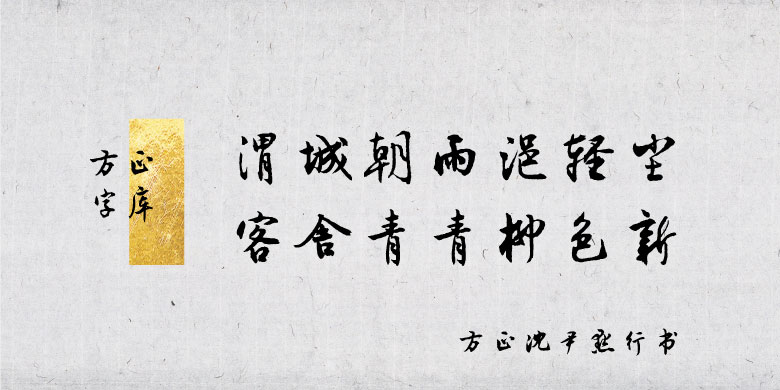
方正沈尹默行书 简繁
字體介紹:
沈尹默(1883-1971),當代書法家、詩人。原名君默,字中,號秋明,浙江吳興(今湖州市)人。早年曾留學日本,解放前曾任北京大學文學系教授,北平大學校長。建國後任中央文史館副館長等,上海市人民委員會委員,第三屆全國人大代表。工正行草書,由以行書著名。初學褚遂良,後遍習晉、唐諸名家,晚年融會蘇軾、米芾。精於用筆,清圓秀潤中有勁健遒逸之姿。倡導以腕行筆,不主張模擬結構,於筆法、筆勢多所闡發,著有《歷代名家學書經驗談輯要釋義》、《二王書法管窺》、《秋明詩詞》等。
字體特征: 以多種沈尹默墨跡為字形依據。筆法揮灑自如,如行雲流水,自然流暢。結字跌宕起伏,清健秀雅。既古意盎然又具有中和圓融的獨特面貌。
沈尹默(1883年-1971年),原名君默,後改尹默,字中、秋明,號君墨,別號鬼谷子。祖籍浙江湖州,1883年生於陜西興安府漢陰廳(今陜西安康市漢陰縣城關鎮民主街),著名學者、詩人、書法家、教育家。
早年留學日本,後任北京大學教授、北平大學校長、輔仁大學教授,《新青年》雜誌編委。與兄長沈士遠、弟沈兼士合稱“北大三沈”。沈尹默1949年後歷任中央文史館副館長,上海市人民委員會委員,第三屆全國人大代表等職務。
沈尹默以書法聞名,民國初年,書壇就有“南沈北於(於右任)”之稱。二十世紀四十年代書壇有“南沈北吳(吳玉如)”之說。與李誌敏合稱“北大書法史上兩巨匠”。 [1] 著名文學家徐平羽先生,謂沈老之書法藝術成就,“超越元、明、清,直入宋四家而無愧。”已故全國文物鑒定小組組長謝稚柳教授認為:“數百年來,書家林立,蓋無人出其右者”。已故臺北師大教授、國文研究所所長林尹先生贊沈老書法“米元章(米芾)以下”。北京大學書畫協會會長張辛教授評價:“北大歷史上的名書法家只有章梫、金息侯、羅復堪、沈尹默等寥寥幾人而已,李誌敏是改革開放新時代第壹人。”
方正沈尹默行書
設計師: 楊龍龍